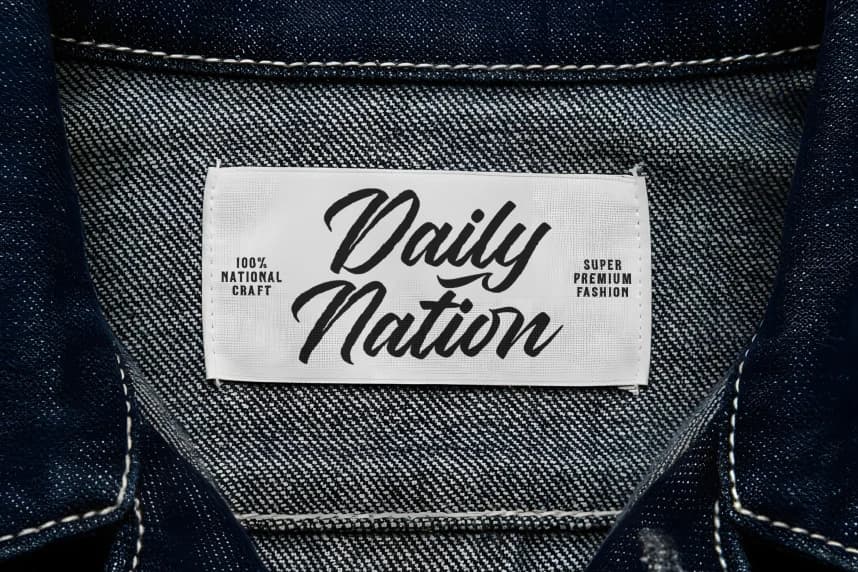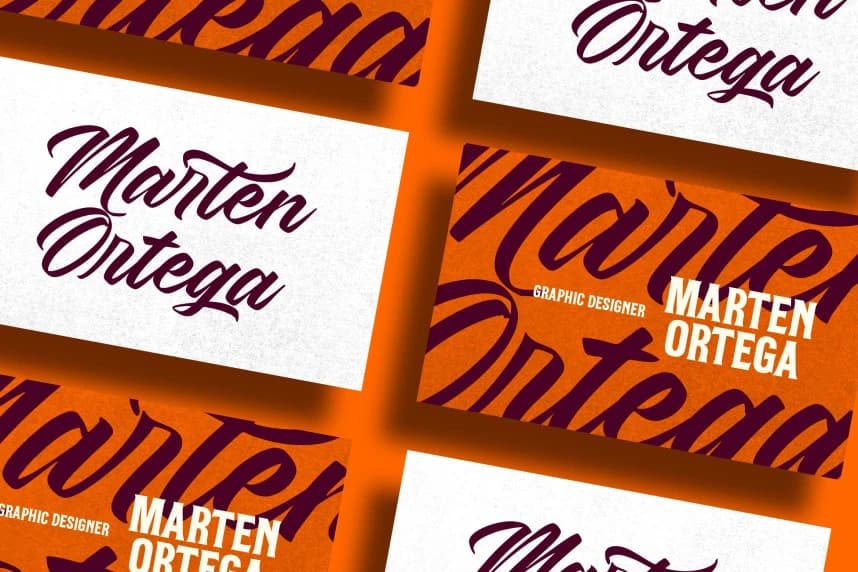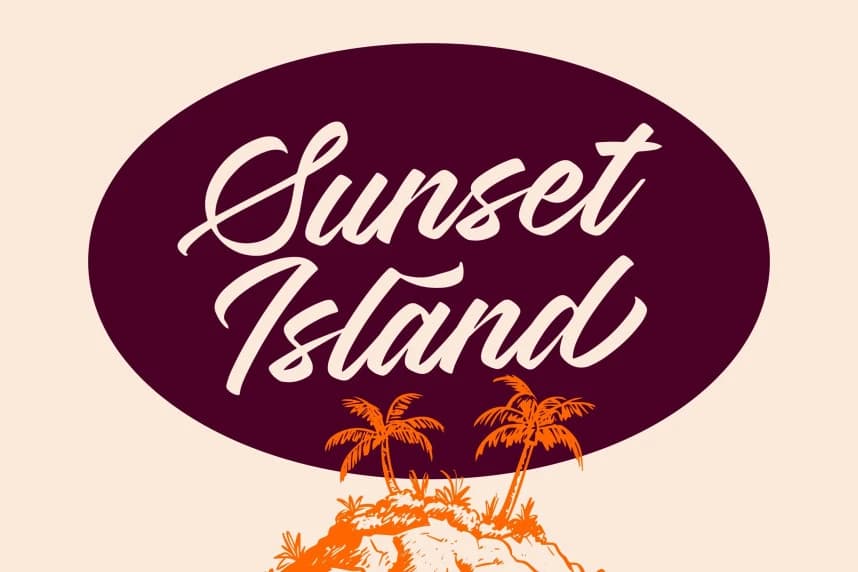
Barty Stones Yazı Tipi
Barty Stones Font, vintage yolculuklardan ve retro tabelalardan esinlenen kalın ve ifadeli bir el yazısı fontudur. Yumuşak kıvrımları, dinamik çizgileri ve kendinden emin harf yapılarıyla güçlü bir görsel varlık sunar ve anında dikkat çeker.
Barty Stones Font, nostaljik yolculuklar ve retro tabelalardan ilham alan cesur ve ifade gücü yüksek bir kaligrafik yazı tipidir. Yumuşak kıvrımları, dinamik çizgileri ve kendine güvenen harf biçimleriyle anında dikkat çeken güçlü bir görsel etki sağlar.